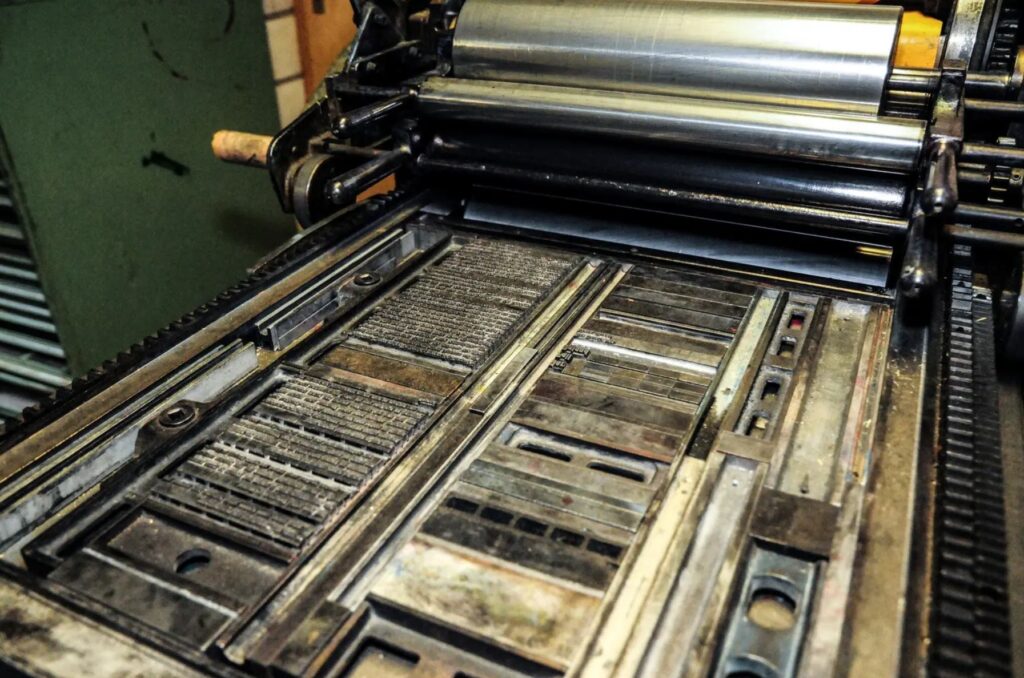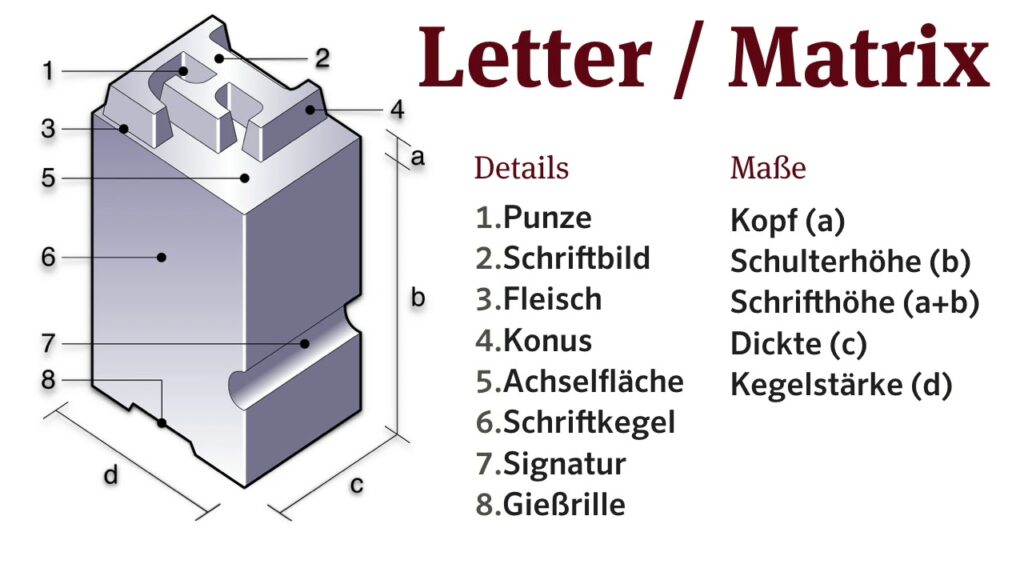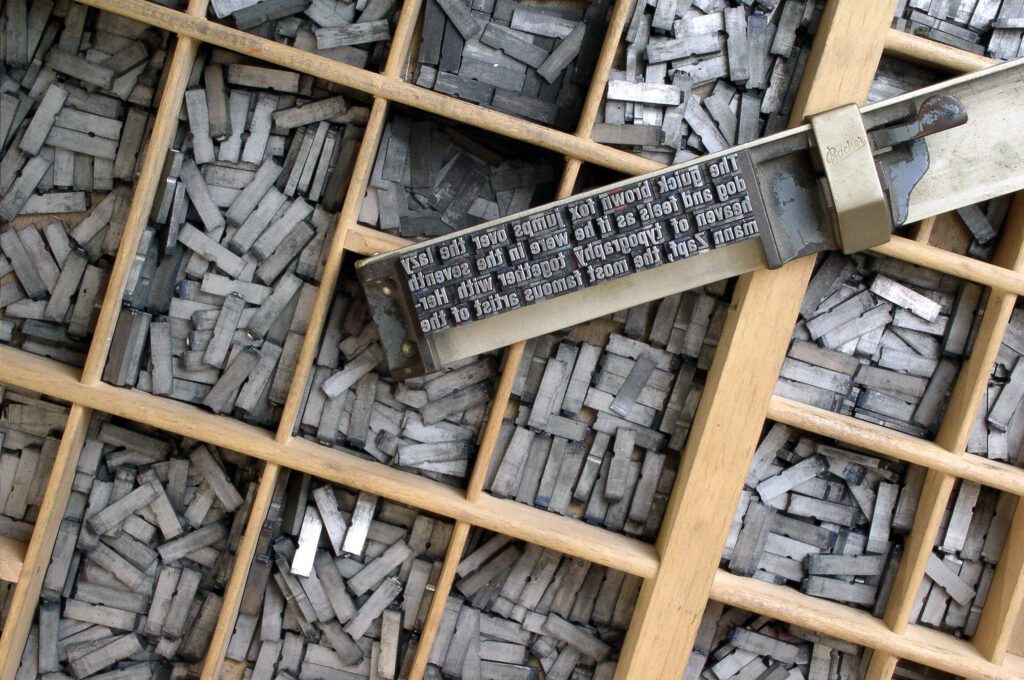
Druckletter – Dickte – Schriftzeichen
Grundlegende Begriffe der Letter
• Letter / Druckletter – einzelne gegossene Bleiletter im Handsatz (enthält Schriftzeichen).
• Schriftzeichen – grafisches Zeichen einer Schrift (Buchstabe, Zahl, Satzzeichen, Sonderzeichen).
• Zeichen – kleinste Einheit der Typografie, die Bedeutung transportiert.
Breite & Raum eines Schriftzeichens (Dickte)
• Dickte – gesamte Breite eines Buchstabens inkl. Vor- und Nachbreite; definiert den „Kegel“ im Bleisatz.
• Buchstabenbreite (Character Width) – sichtbare Breite des Zeichens ohne Seitenräume.
• Vorbreite (Side Bearing / Linke Dickte) – Abstand vom linken Rand der Letter zum Beginn des Zeichens.
• Nachbreite (Side Bearing / Rechte Dickte) – Abstand vom Ende des Zeichens bis zum rechten Rand.
• Schriftkegel (Type Body) – rechteckiger Block des Bleibuchstabens, auf dem das Zeichen sitzt.
• Dicktenbreite – Maß der Letter in der Breite, beeinflusst Satzbild und Zeilenfall.
• H-Kegel – Standardmaß für Schriftkegel (z. B. 12 Punkt).
Abstände & Spationierung
• Spatium – Zwischenraum, Leerstück, aus Metall (verschiedene Dicken).
• Geviert (Quadrat) – Grundquadrat im Bleisatz, Breite = Schriftgröße.
• Halbgeviert – halbe Breite des Gevierts (z. B. für Gedankenstrich).
• Viertelgeviert – Viertelbreite des Gevierts (z. B. schmale Leerzeichen).
• Spationierung – Einfügen zusätzlicher Abstände zwischen Buchstaben (Sperrung).
• Sperren – gezieltes Auseinanderziehen von Buchstaben durch Spatien.
• Unterschneiden (Kerning) – Reduzierung von Zwischenräumen zwischen kritischen Zeichenpaaren (z. B. „AV“).
• Laufweite (Tracking) – gleichmäßige Änderung aller Abstände in einem Textabschnitt.
• Ligatur – Verschmelzung zweier oder mehrerer Buchstaben zu einem Zeichen (z. B. „fi“, „fl“).
Digitale Entsprechungen
• Monospace-Schrift – jede Dickte gleich breit (z. B. Schreibmaschinenschriften).
• Proportionale Schrift – unterschiedliche Dickten pro Zeichen.
• Advance Width – metrische Dickte in digitalen Fonts (Breite eines Zeichens mit Side Bearings).
• Bounding Box – rechteckige Umgrenzung des Zeichens (technisches Maß im Font).
• Em-Width (Em-Quadrat) – digitale Entsprechung des Gevierts (meist 1000 Font Units).
• Side Bearings – digitale Vor- und Nachbreiten im Font-Metriksystem.
Weitere historische Begriffe
• Fleisch – unbedruckte Fläche um das Zeichen auf der Letter.
• Kegelgröße – Höhe des Schriftkörpers (z. B. 8p, 12p).
• Überhang (Overshoot) – kleine optische Korrektur, wenn runde Zeichen leicht über die Kegelbegrenzung hinausragen.
• Spitz (Punzen) – Innenräume von Buchstaben (z. B. „a“, „o“).
• Gießinstrument – Werkzeug, mit dem Dickten im Bleisatz festgelegt wurden.